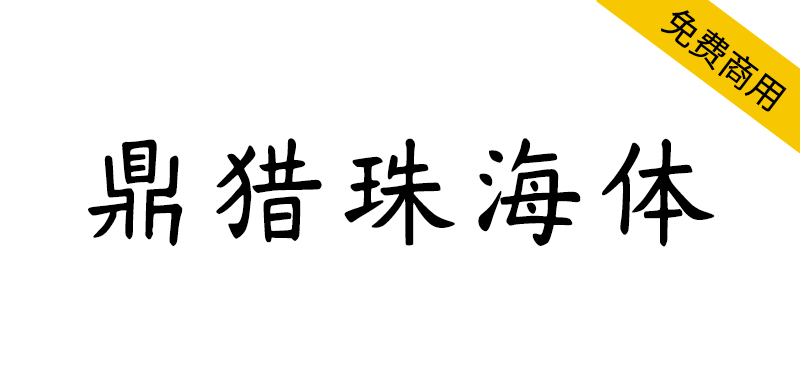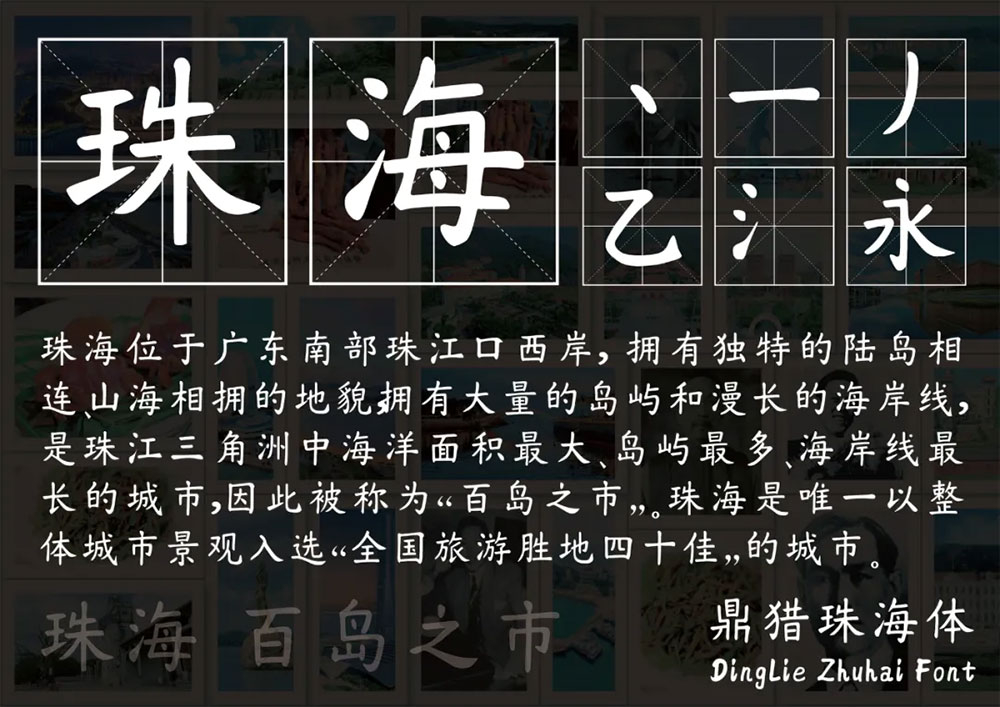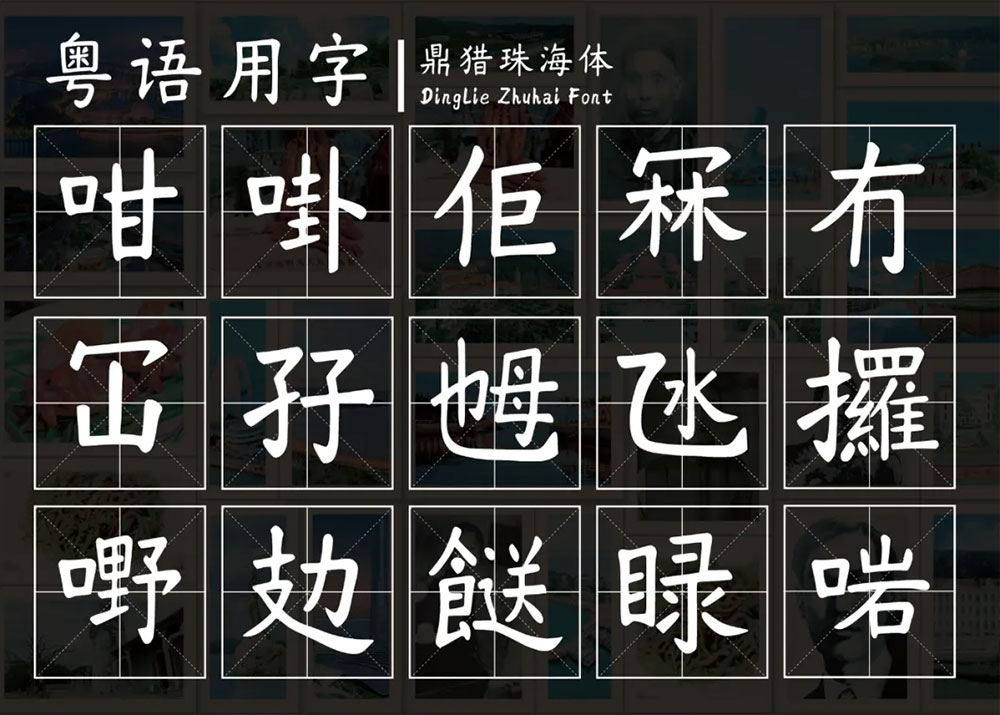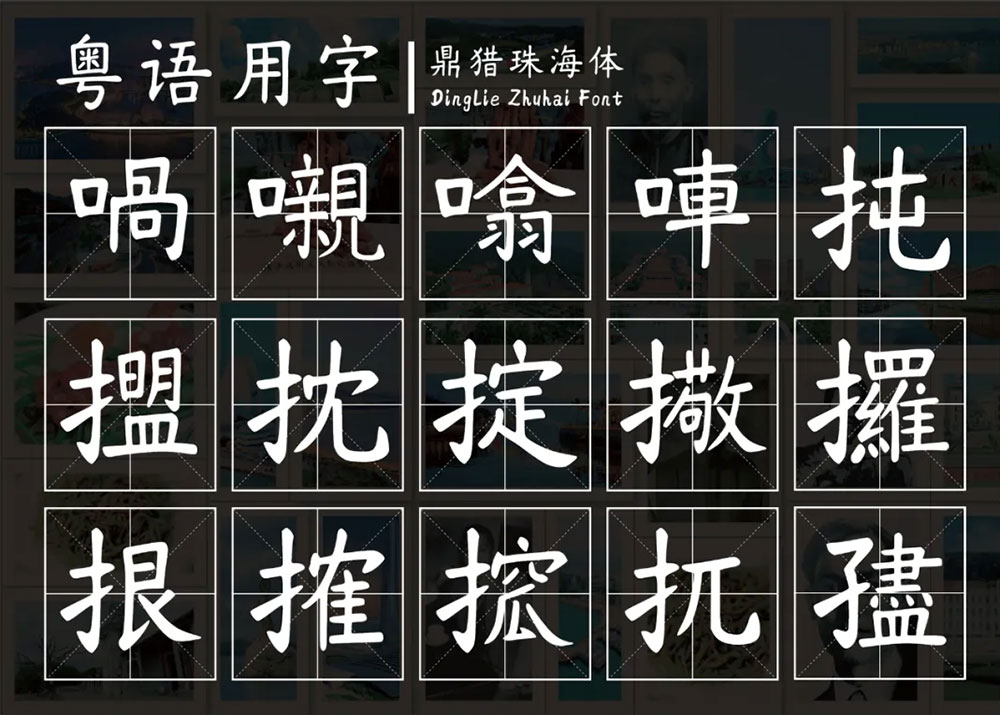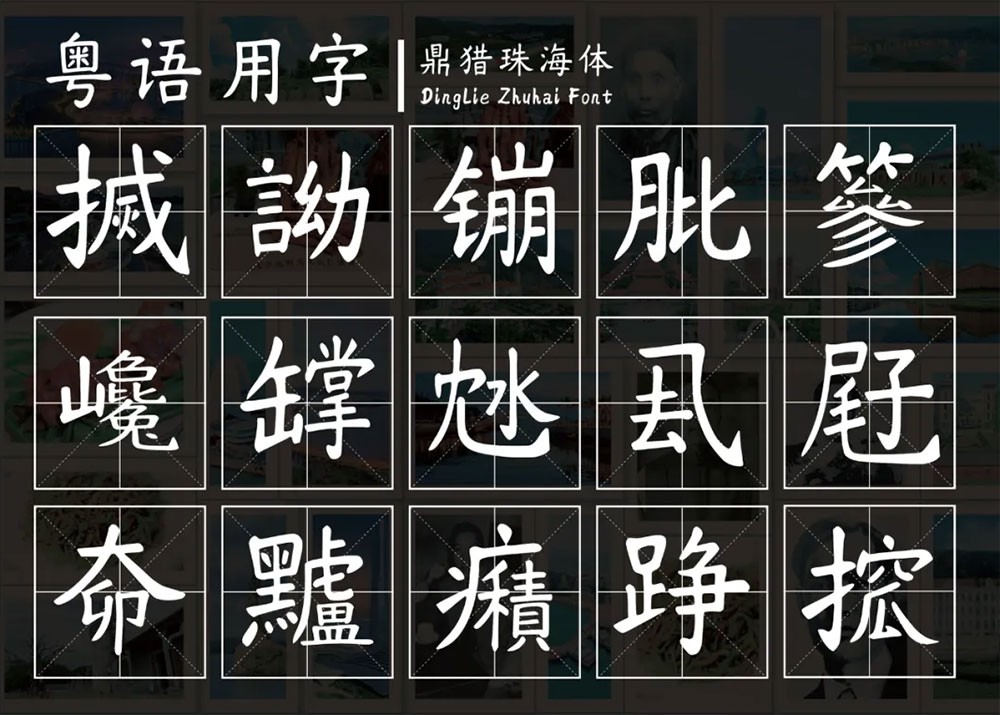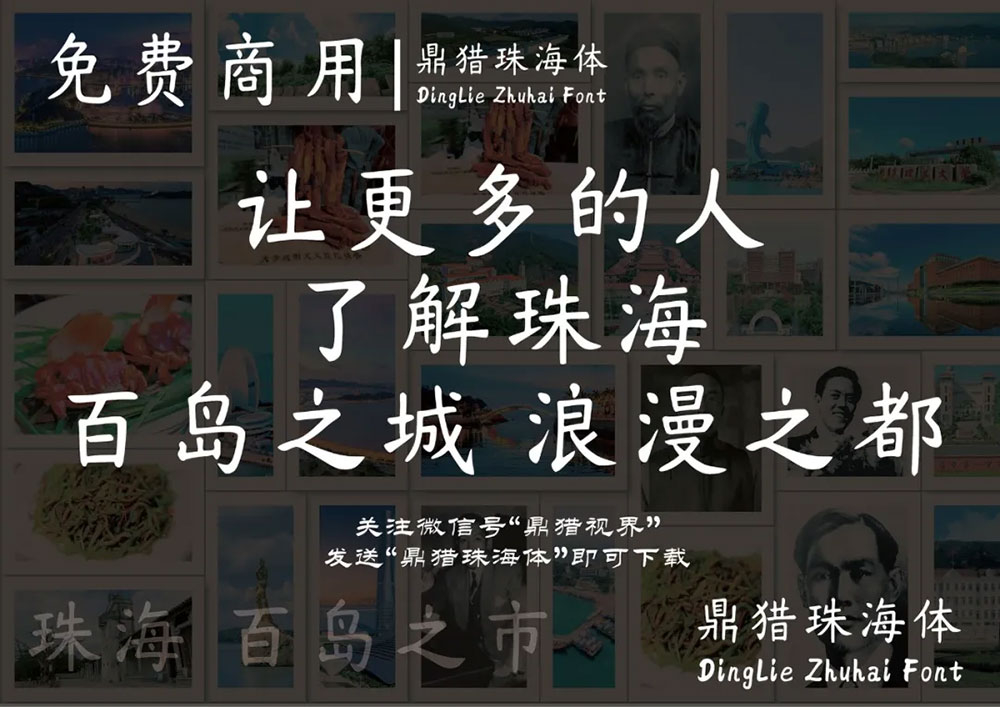
鼎猎咨询作为一家珠海本土企业,希望能创造一套以“珠海”命名的专属字体,以此助力这座浪漫之都、旅游之城,带着珠海特有的文化和故事,传播得更远、更广。让更多的朋友来珠海游玩、定居。这套字体姗姗来迟,终于到了发布的时候。
这是一套融入了珠海特质的字体 — 鼎猎珠海体,以珠海先贤苏曼殊墨宝,“金玉良言常佩带,芝兰浓馥振精神。”为缘起。
考虑到珠海位于粤港澳大湾区,以简体中文汉字编码国家标准(GB2312)为标准,共计设计了多达7905个字符,其中汉字6916个。在6763个汉字基础上,特别增加了153个常用粤语汉字,可以满足绝大部分印刷设计等要求。